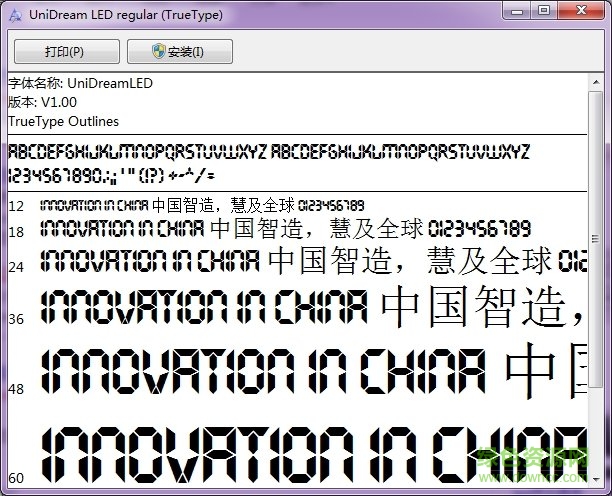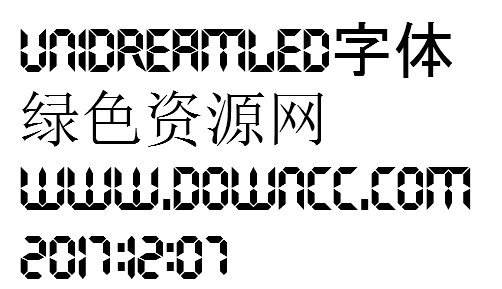
unidreamled字體是一款液晶電子表字體,是我們常見(jiàn)的led屏幕中出現(xiàn)的數(shù)字字體,對(duì)于數(shù)字文字的使用上有著極佳的顯示效果,有需要的朋友就來(lái)綠色資源網(wǎng)體驗(yàn)吧!
unidreamledregular常見(jiàn)于電子顯示屏、計(jì)算器、鐘表等儀器設(shè)備上,使我們接觸比較多的字體,unidreamled字體清晰醒目,造型端正嚴(yán)謹(jǐn),是使用廣泛的阿拉伯?dāng)?shù)字字體,也叫液晶字體、數(shù)字字體、電子表字體等。
unidreamled字體,很方便的顯示數(shù)碼管數(shù)字,該字體的靈感來(lái)自于古老的LCD顯示器,美觀的界面,可以廣泛運(yùn)用于藝術(shù)設(shè)計(jì)、屏幕設(shè)計(jì)、廣告設(shè)計(jì)等諸多領(lǐng)域,給用戶帶來(lái)非常好的體驗(yàn)。